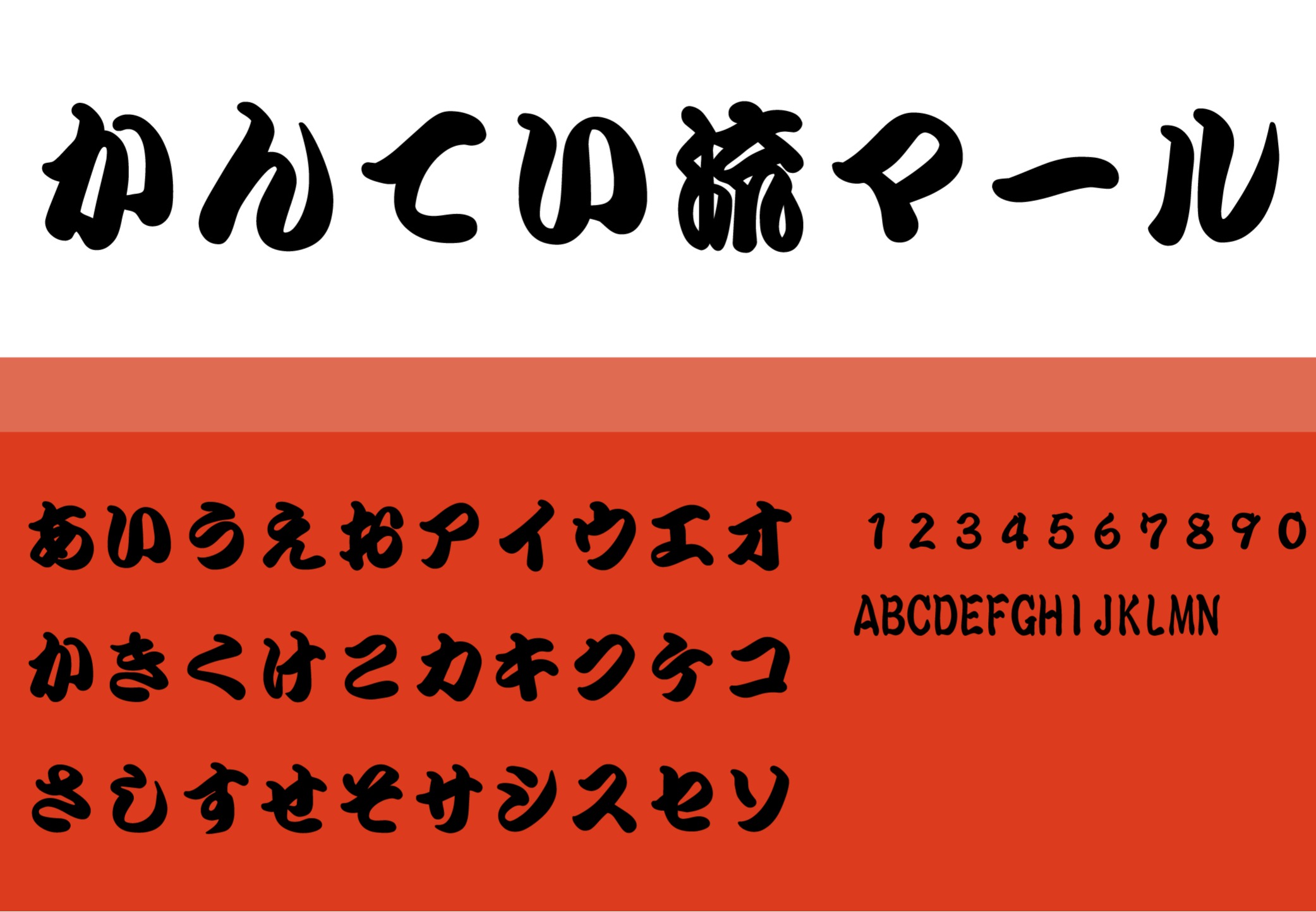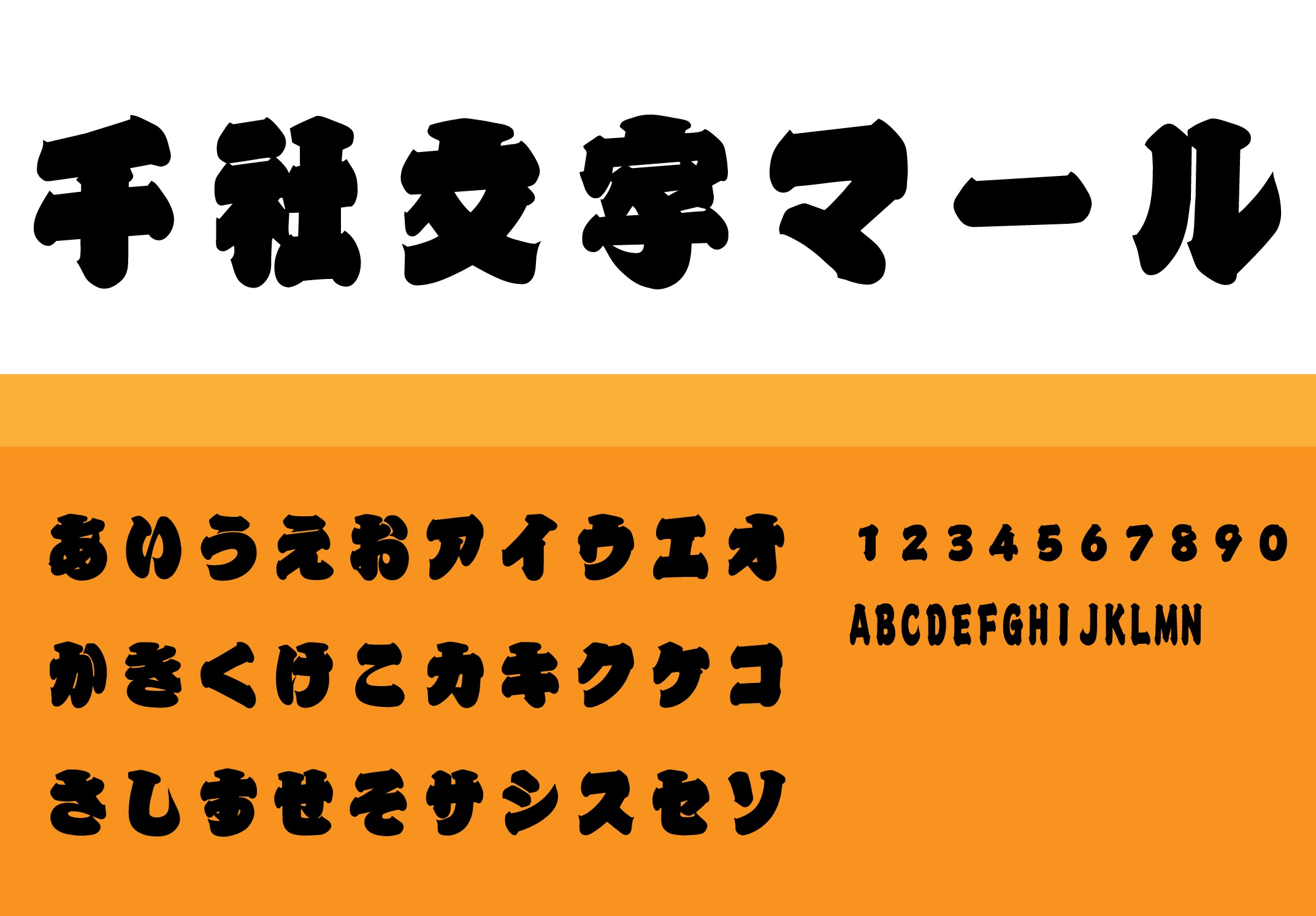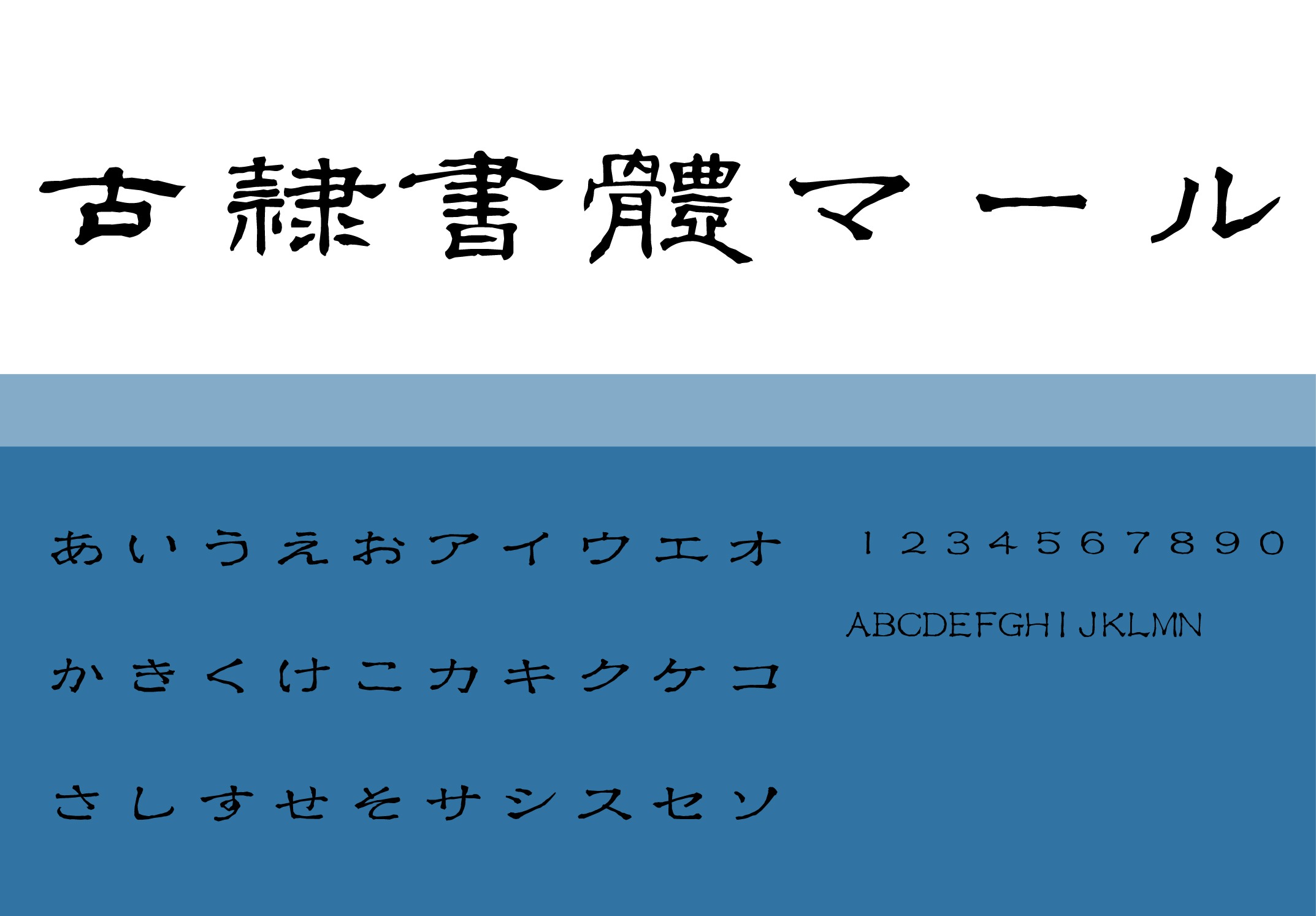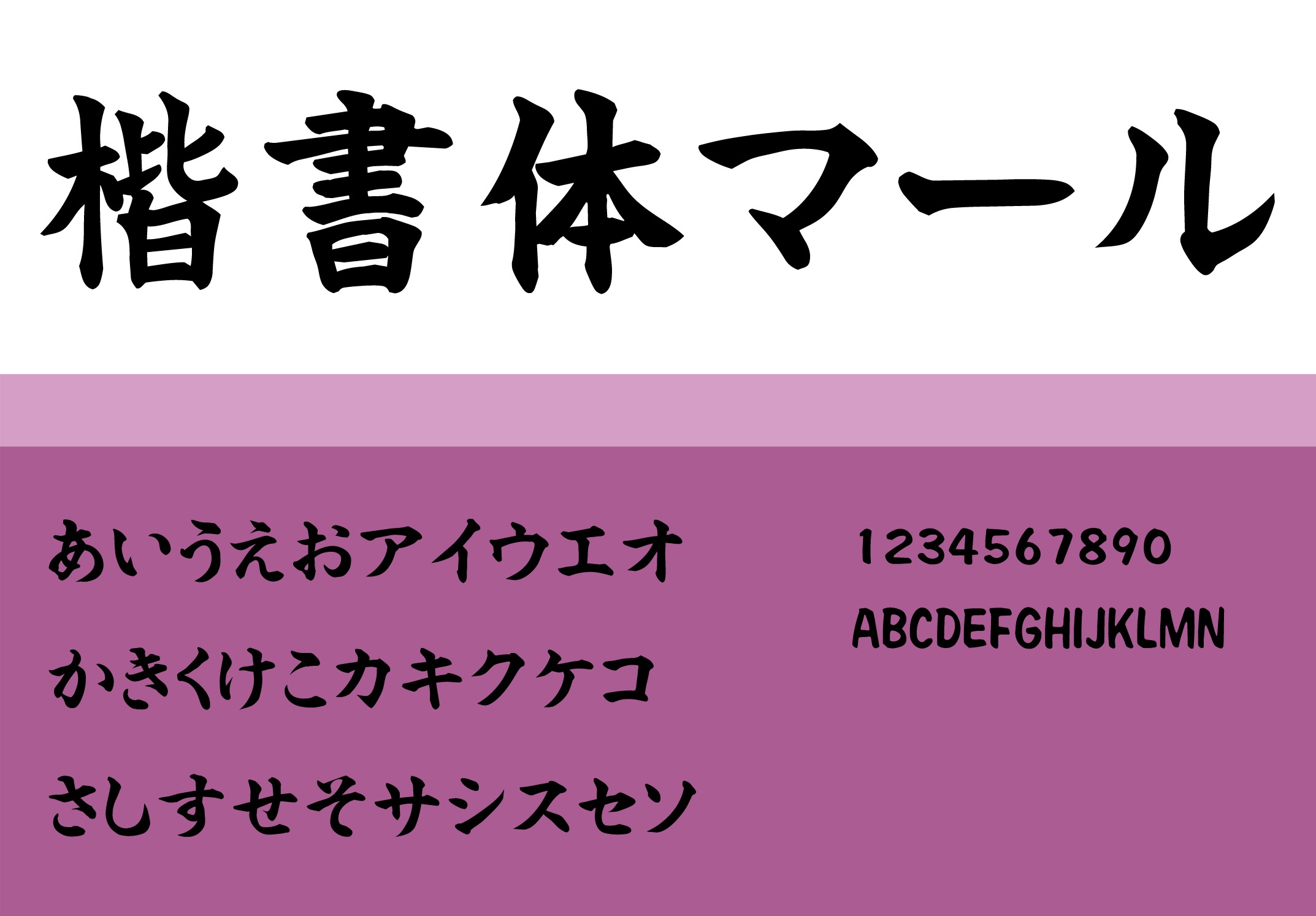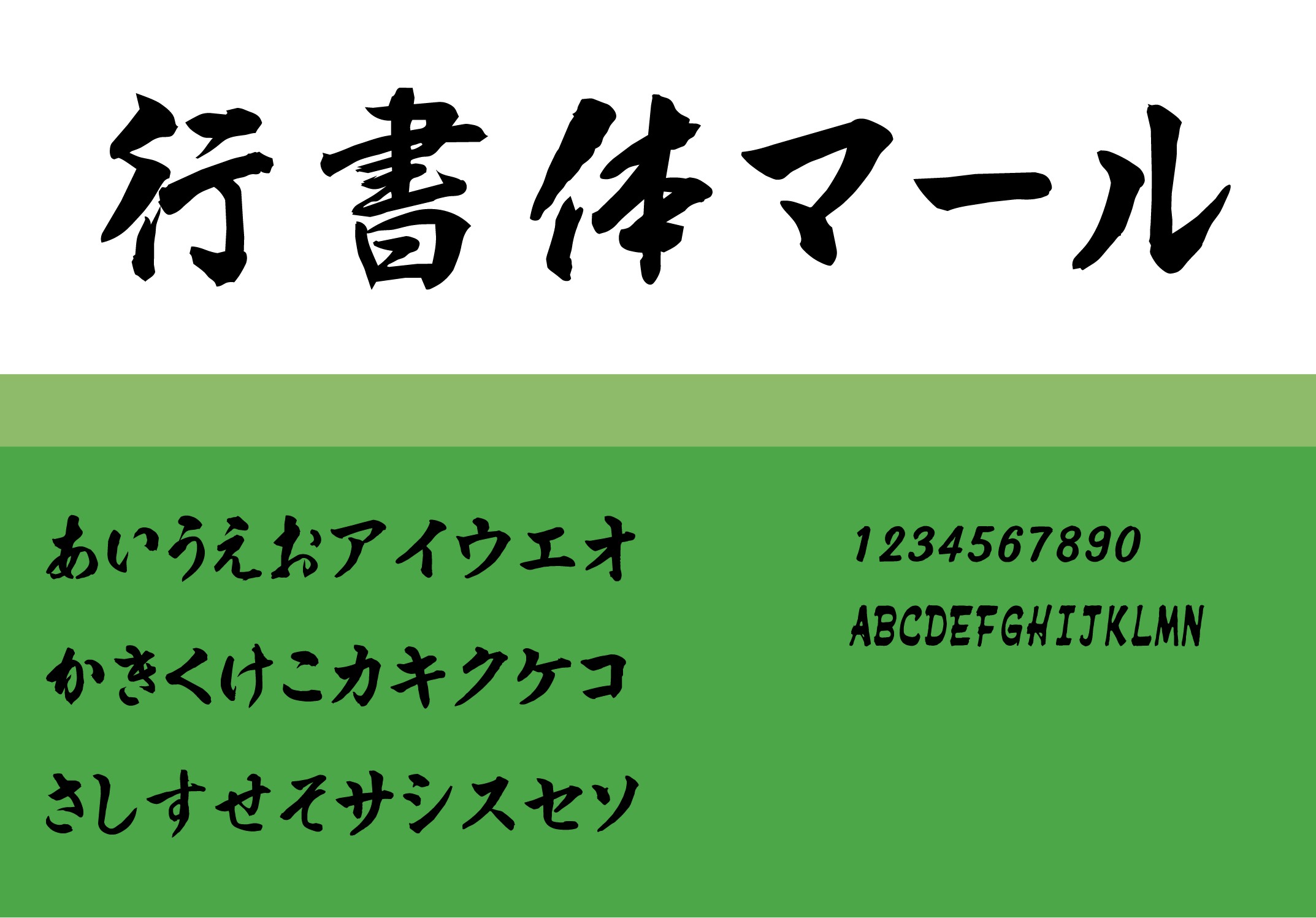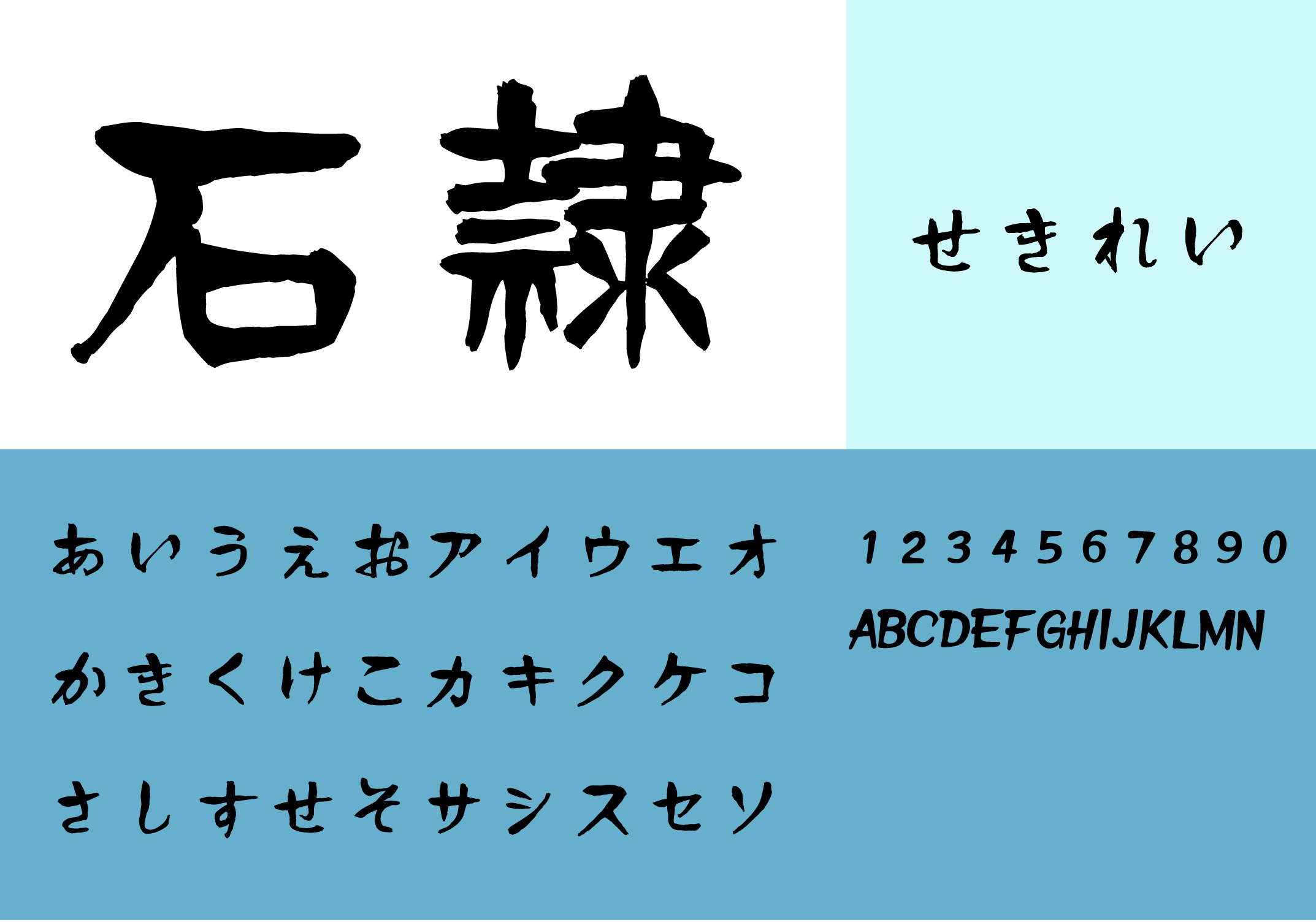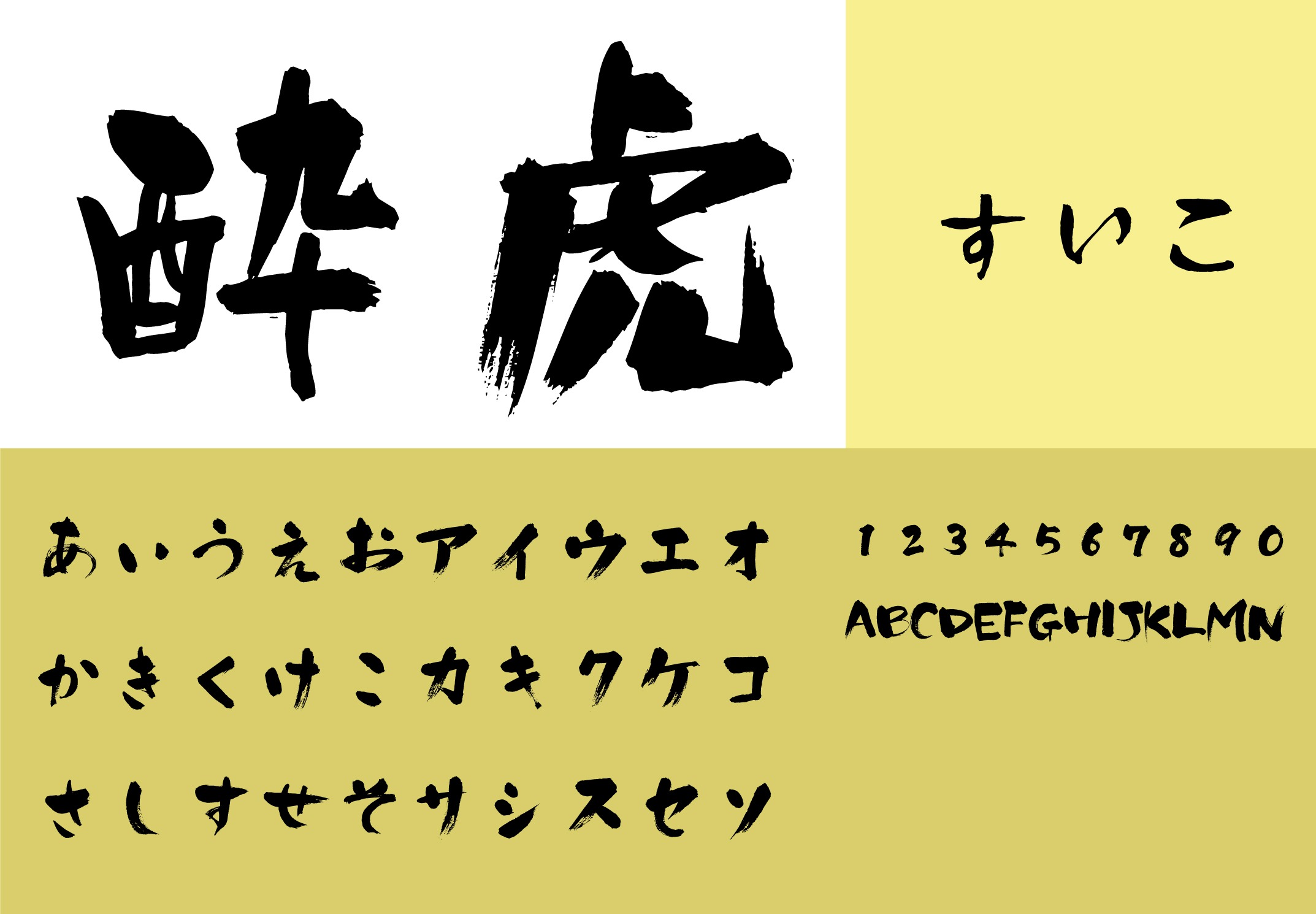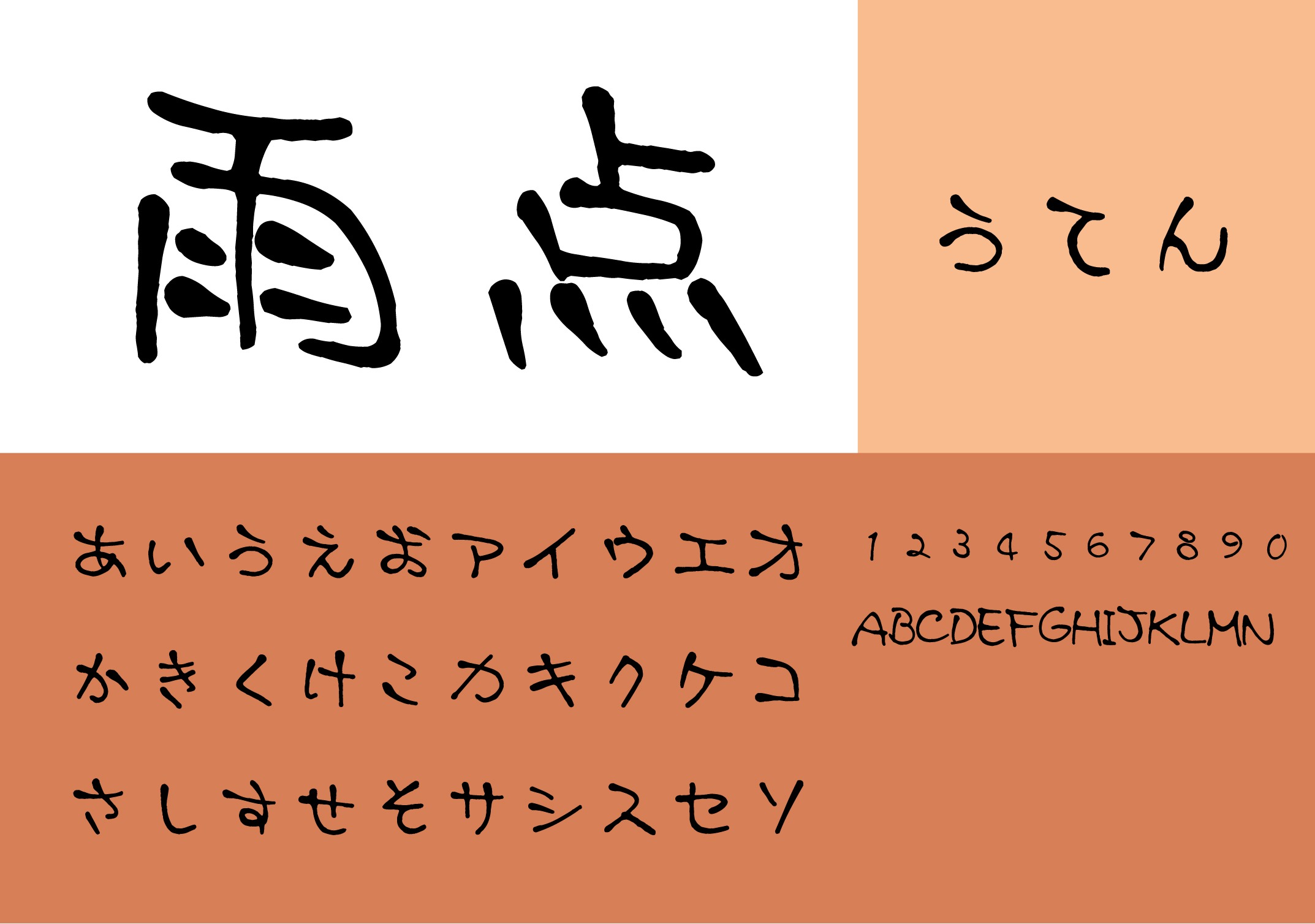
書体デザイナー 株式会社マール社 日本の出版社 プロフィール マール社は美術・デザイン書、実用書、ビジュアル資料集などを発行している日本の出版社です。書籍で刊行していた広告用書体シリーズ「ディスプレイ書体シリーズ」「デザイン筆文字シリーズ」のうち、特に特徴ある書体をフォント化いたしました。楷書体や行書体、かんてい流や千社文字など多彩なラインナップをお楽しみ頂けます。 さらに詳しく閉じる 代表フォント 制作フォント Can't login